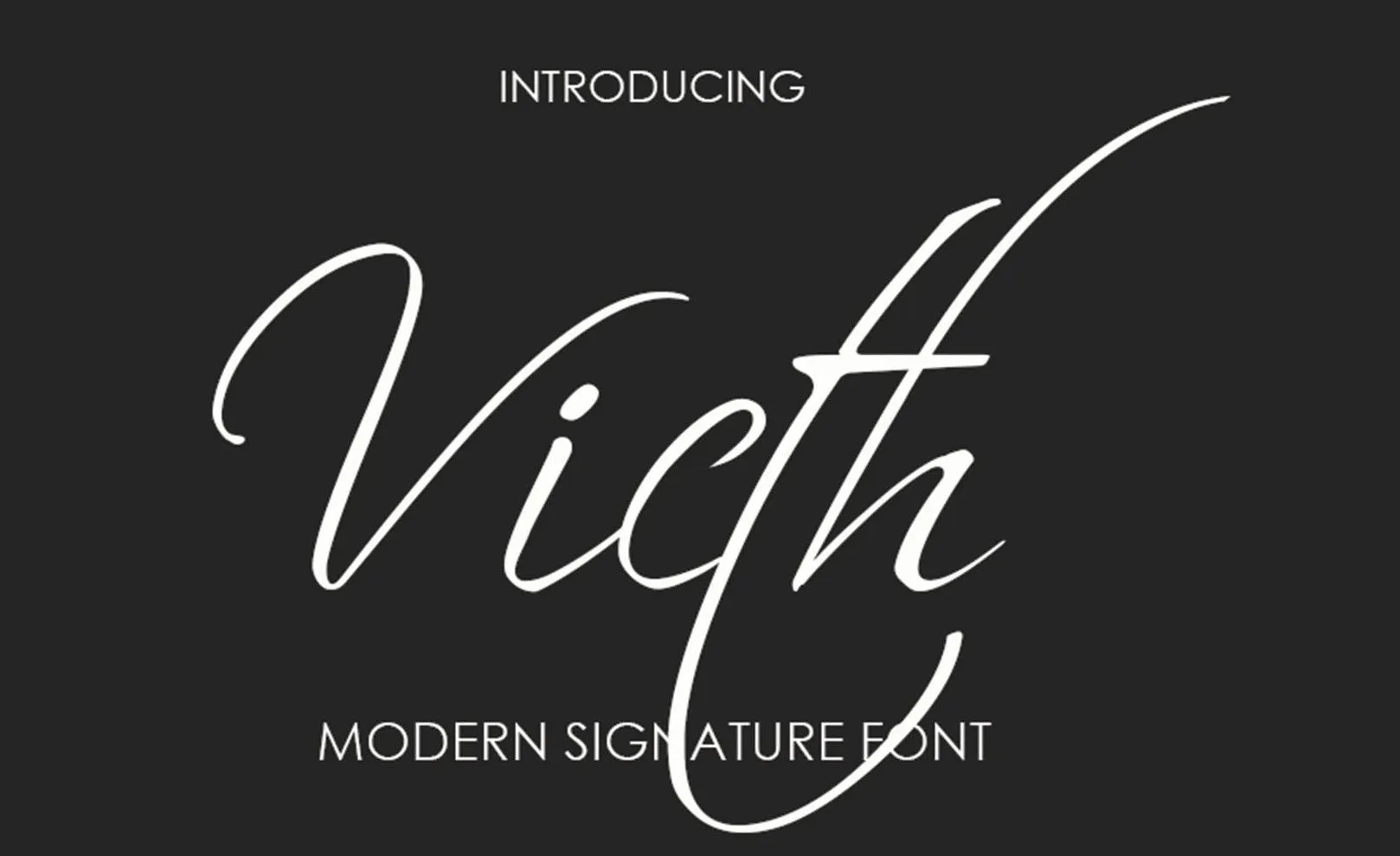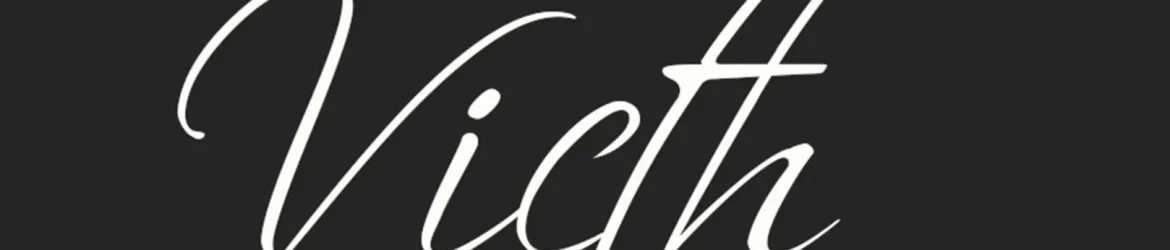
Victh Signature Font – Download Grátis
Victh Signature Font é uma opção perfeita para quem busca personalidade e delicadeza em seus projetos tipográficos. Este é um tipo script relaxado que se destaca por sua beleza única e versatilidade, ideal tanto para títulos quanto para detalhes pessoais como assinaturas, logotipos, cartas de correspondência, convites de casamento, formulários, rótulos, mensagens em anúncios, símbolos de presença, marcações ou identificações corporativas. Com sua linha perfeita e estilo de assinatura, esta fonte se destaca como uma opção elegante para vários usos cotidianos, oferecendo um toque único que tornará seus projetos ainda mais interessantes e atraentes.